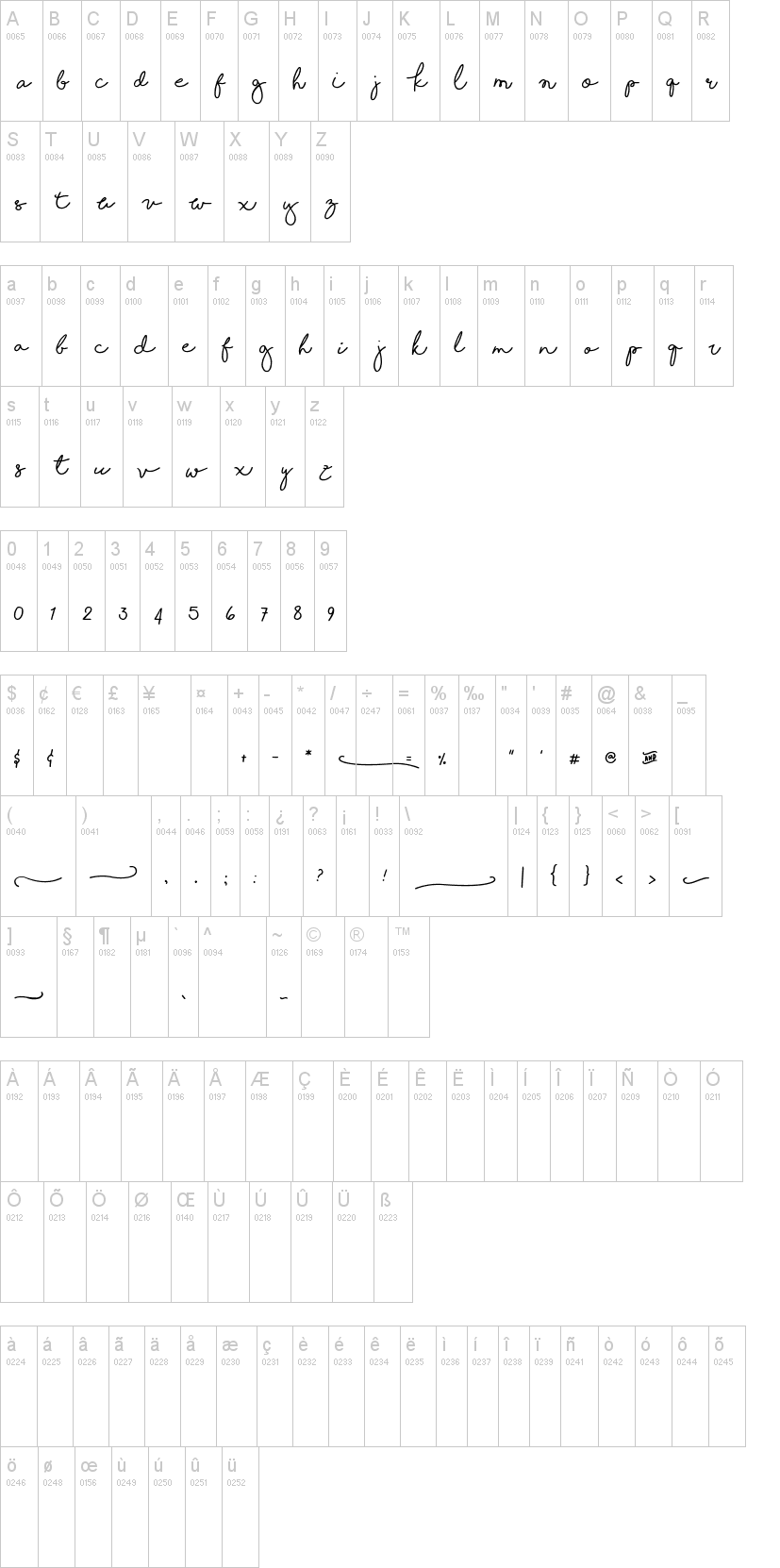
Shorelines Script 是一款漂亮的手写字体,它具有柔和、优雅的外观,可以给您的设计带来温暖的感觉。它的主要特点是拥有流畅的笔画,它的字体结构简单,易于识别,拥有大量的曲线笔画,可以使您的设计更加有趣。它的字符设计也特别的精致,拥有许多可爱的小细节,可以给您的设计增添一份独特的魅力。内容介绍
Shorelines Script是一款非常不错的手写艺术字体,具有很好的视觉感,适合于文化类的宣传设计、商业类品牌的广告和产品包装设计以及个性化文字排版等较多场景。